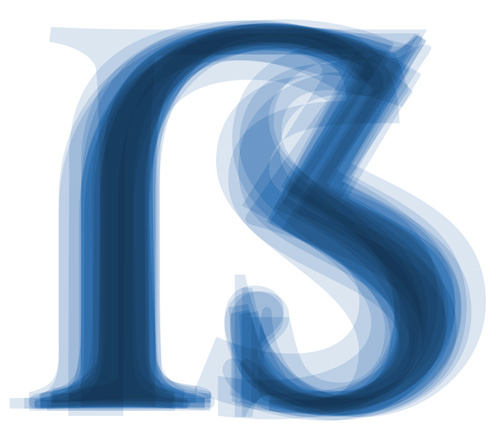
Am kommenden Samstag präsentieren Nadine Roßa und Ralf Herrmann ihre international gewürdigte Präsentation »Das kleine und das große Eszett« im Berliner Buchstabenmuseum, um 14:00 Uhr, Eintritt 2,50 €. Schon die verschiedenen Namen deuten darauf hin, dass das ß ein ganz besonderer Buchstabe ist: scharfes S, Buckel-S, Rucksack-S, Dreierles-S … Seine gestalterische und funktionale Herkunft ist bis heute nicht restlos geklärt und die Tatsache, dass er in der Orthografie von Deutschland und Österreich benutzt wird, aber bislang keinen offiziellen Großbuchstaben besitzt, macht ihn einzigartig innerhalb der gesamten lateinischen Schrift. Dabei kommt das Eszett selbst im Deutschen nur selten vor – nach der Rechtschreibreform sogar noch weniger. Doch es behauptet sich weiter hartnäckig und kämpft nun sogar wieder verstärkt um eine eigene Versalform.
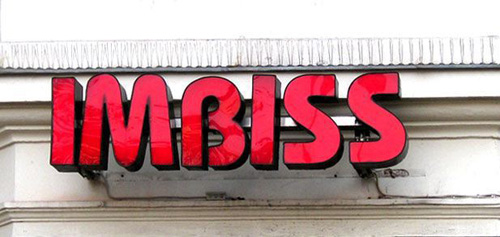
Nadine Roßa und Ralf Herrmann (der in der Stadt Pößneck geboren wurde) schlagen sich mit den Irrungen und Wirrungen um diesen Buchstaben schon ihr ganzes Leben herum. Nadine Roßa trägt diesen Buchstaben heute sogar mit Stolz und widmete ihre Diplomarbeit an der HTW Berlin dem Eszett. Aus dieser Arbeit und ihrem Leben mit dem Eszett im Namen wird sie in diesem Vortrag berichten. Ralf Herrmann führt anschließend in die derzeitige Debatte um Sinn oder Unsinn eines Versal-Eszett ein. Wie konnte es dazu kommen, dass lediglich ein Buchstabe der lateinischen Schrift nicht über eine Versalform verfügt? Und wie ist dieser Umstand im Jahr 2011 zu bewerten? Ist dies eine geschichtlich bedingte Eigenheit oder ein Grund zu handeln? Welche Gründe sprechen heute für oder gegen die Etablierung eines großen Eszett?
The never ending story…. Mal unabhängig davon, ob es sich bei der Frage des ›großen Eszett‹ um eine sprachliche oder um eine typografische handelt, und auch unabhängig von der Diskussion, ob ›der Gestalter‹ problematische Situationen nicht auch ohne großes Eszett lösen können sollte oder müsste, muss ich sagen, dass die sich derzeit einschleichende Form (von R.H. basierend auf historischen Vorschlägen forciert) des versalen Eszett extrem suboptimal ist – und zumindest ästhetisch das ß-Problem nicht löst. Die Form ist zu ›komplex‹ (Stamm, großer Bogen, Diagonale/Schräge, Bauch), schlägt zu viele Haken und verursacht obendrein weiterhin zu große Löcher in die jeweiligen Wortbildern. Hier gilt es sicherlich noch einmal auf die Suche zu gehen und die schriftgestalterischen Möglichkeiten (historisch, ästhetisch etc.) auszuloten! (Vielleicht könnte man hier, ähnlich wie beim Rupien-Symbol, einen Wettbewerb starten!?)
Vielleicht könnte man sich auch einmal das Posten verkneifen. Der Zug ist doch schon vor einer ganzen Weile abgefahren.
Eben. Wer sich für das Thema interessiert, weiß, daß sich das Antiqua-ß bis auf 1667 zurückführen läßt und die früheste Versal–Eszett–Type auf 1879…
Seit dem 04.04.2008 ist das große Eszett im Unicode vertreten, seit 23.06.2008 auch in ISO/IEC 10646. Diskussion unnötig.
tatsächlich? diskussion unnötig? interessanter ansatz … unicode befiehlt und wir folgen?
aber ja, leider ist der zug abgefahren und dümpelt nun auf dem völlig falschen gleis dahin um mal bei der metapher von andreas zu bleiben.
ich finde die energie, die ralf und nadine jetzt da erneut reinstecken ja großartig, aber ich bin mir sicher, beide haben auch noch jede menge andere themen von mehr relevanz im schrank liegen.
Wird das große ß tatsächlich irgendwo verwendet? Mir kommt es vor wie eine Lösung, die nach einem Problem sucht.
Ralf und Nina leisten da hervorragende Arbeit für präzise Typografie, auch wenn ich mit der Glyphe nicht so richtig warm werde. Mir fehlt da der Versalcharakter, aber diese Diskussion ist nach dem festen Unicode-Platz wirklich gelaufen. Das Zeichen ist in der Welt, jetzt muss es sich behaupten. Ich bin froh, dass ich »Viel Spaß« hier gemischt schreiben kann… :)
was soll das bringen? dann erhalten wir ein ergebniss der form und jeder schriftgestalter bastelt dann trotzdem seine eigene form. ähnlich wie beim dem konstruierten eurozeichen.
sicher ist die form komplex, allerdings bezieht sich das ja auch auf das kleine ß und hier gibts ja mittlerweile ein paar passende beispiele das es möglich ist das zeichen umzusetzten. ;) natürlich liegt es immer am schriftgestalter selbst was er draus macht, hier auch nochmal der blick zum € und @. ähnlich komplex, jedoch wurden größtenteils gut gelöste formen gefunden.
ich muss zugeben, auch als befürworter des versal-ß (auch wenn ich konsequent kleinschreibe) finde ich viele lösungsvorschläge eher GROBARTIG als großartig – aber wie gesagt: hier sind die schriftgestalter gefragt passende lösung zu finden. deshalb leistet ralf diese aufklärungsarbeit.
Mit Unicode und DIN hat das nichts zu tun. Es ist Aufgabe der Schriftsetzer und Typografen, sich über das Versaleszett Gedanken zu machen. Der Bedarf ist doch objektiv gegeben, weil Eigennamen Eszetts enthalten und in der Datenverarbeitung nicht selten in Versalien geschrieben werden, und zwar von Behörden. Das sind genau diejenigen, denen die amtliche Rechtschreibung das Versaleszett in ihrer geltenden Fassung von 2006 verbietet. Dort ist Eszett als Versal in SS aufzulösen und alles andere falsch.
Bedauerlicherweise ist die kluge Herr Forssmann als einziger Schriftsetzer aus dem Rechtschreiberat ausgeschieden. Er enthält jetzt nur noch Germanisten, die in der Sprachwissenschaft nicht gerade zur Kröm de la Kröm gehören.
Es spielt auch keine Rolle, wie alt die Idee des Versaleszetts ist. Wenn die Zeit gekommen ist, wird es eben erfunden. Und das ist Aufgabe der Typografen. Im Isländischen hat man ganz unkompliziert den Versal Ð erschaffen, der wie das Eszett nie am Wortanfang vorkommen kann.
Wie das Versaleszett dann aussieht, ist die Entscheidung der Schriftentwickler. Auch die Minuskeln a und g haben ja geschlossene und geöffnete Formen, je nach Schrift. Genormt muß das nicht werden.
Der Antrag zur Unicode-Aufnahme des großen Eszetts stammt von Andreas Stötzner, er hat auch die sog. Leipziger Form vorgeschlagen. Herr Stötzner hat sich über die Form viele Gedanken gemacht und die schriftgestalterischen Möglichkeiten ausführlich ausgelotet. In SIGNA Nr. 9 ist das nachzulesen: eine Pflichtlektüre für alle, die beim großen Eszett mitreden wollen.